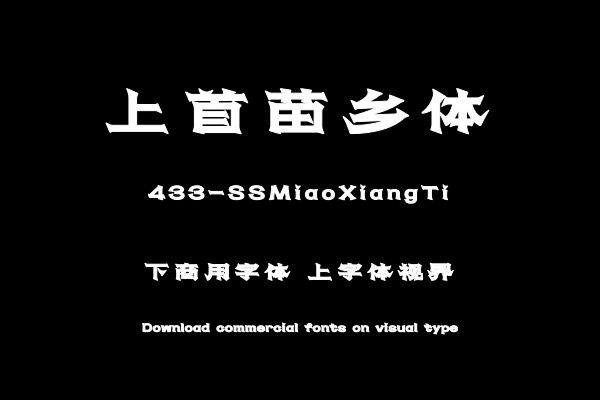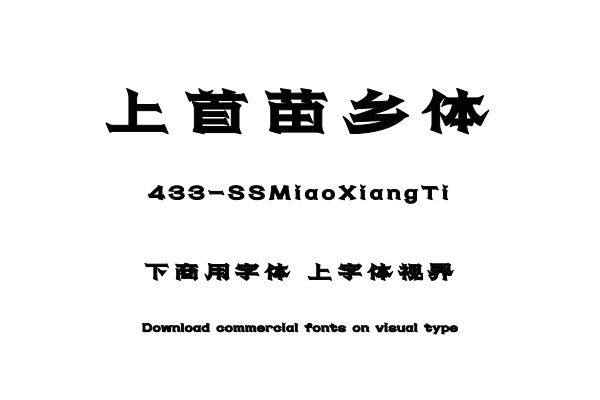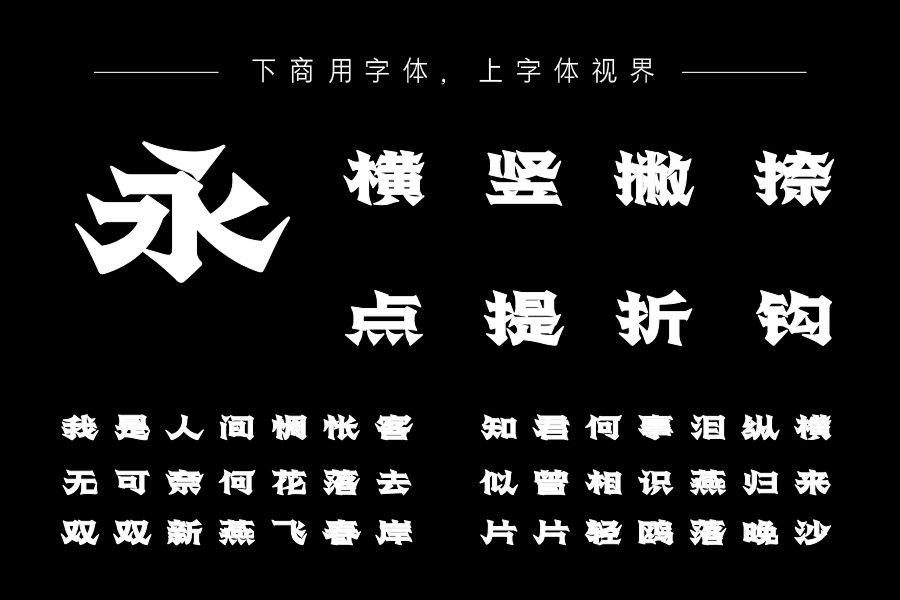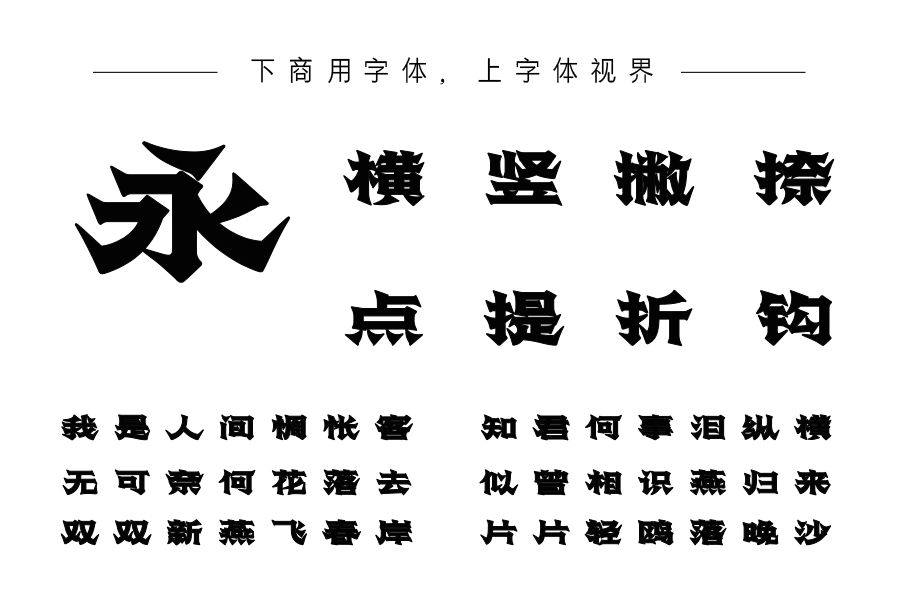
上首苗乡体,简体中文约6763字,字体笔画融入了苗族银饰元素及建筑风格的特点,增加了字形修饰度,丰富字体形态,诠释文化与民族融合的独特魅力。适用于搭配标志、广告......购买须知:“下载服务费”与“字体VIP”所获得字体 仅用于个人非商用, 商用请联系付费授权。本字体为电脑用字,手机没有root权限不支持直接手机换字(手机如何root,请自行百度搜索教程)。购买前请先 了解清楚后再付款 ,字体为虚拟产品无法回收 一旦购买不支持退款。